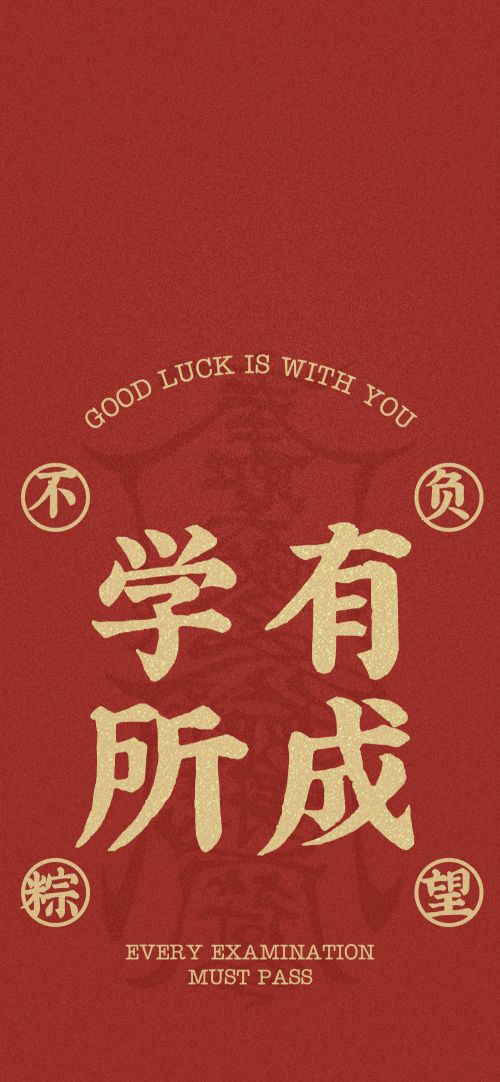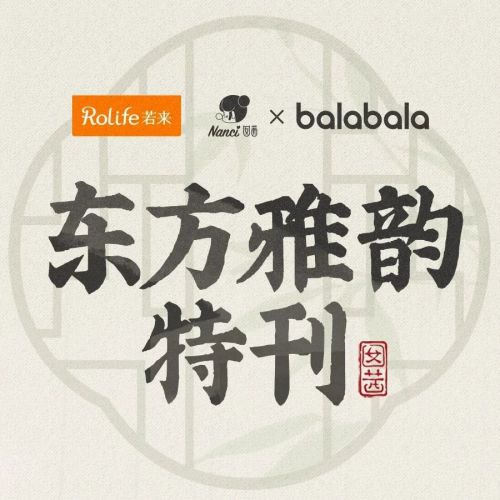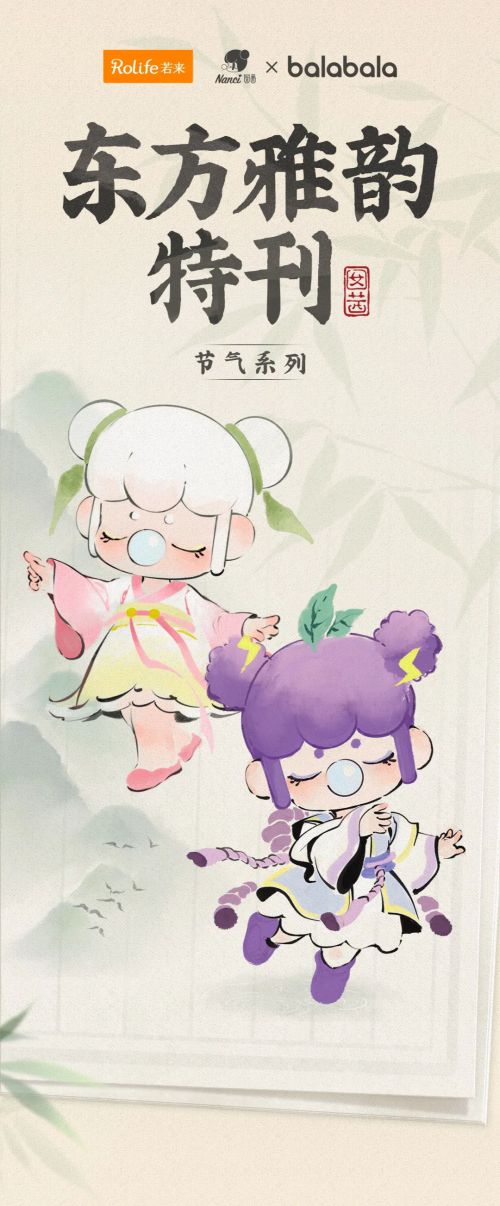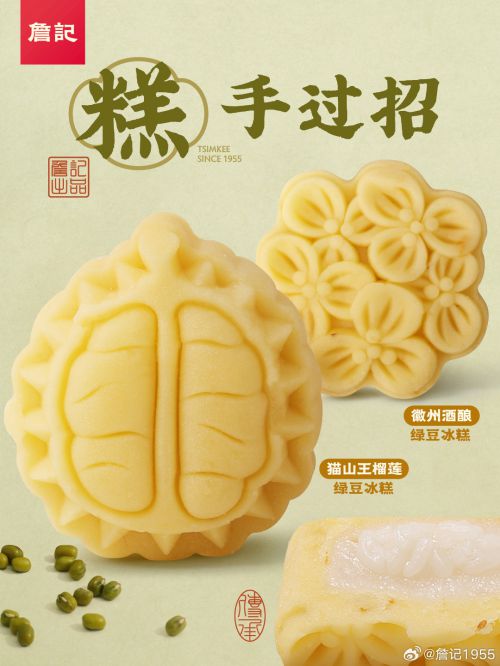
点字五经明刻本
点字五经明刻本是点字库推出的一款中国风古典楷体字体,以明代翁溥校订的魁本大字《五经》为复刻蓝本,将儒家经典《诗》《书》《礼》《易》《春秋》的千年文化底蕴熔铸于字形之间。字体结构方正端庄,重心居中平稳,中宫松紧适中,既延续古籍刻本的严谨排版法度,又通过现代技术优化了笔画间距,适配多场景阅读需求。 点字五经明刻本笔型设计极具辨识度:采用利落直角勾勒轮廓,方头笔画粗重饱满且粗细均匀,笔画连接处清晰断开,复刻出明代刻本“刀刻般”的古朴质感。其字形保留了原典“力透纸背”的书法韵味,搭配会员商用授权,适用于古籍复刻、传统文化主题海报、书法艺术展示等场景,让设计作品自带经典传承的厚重与雅致。